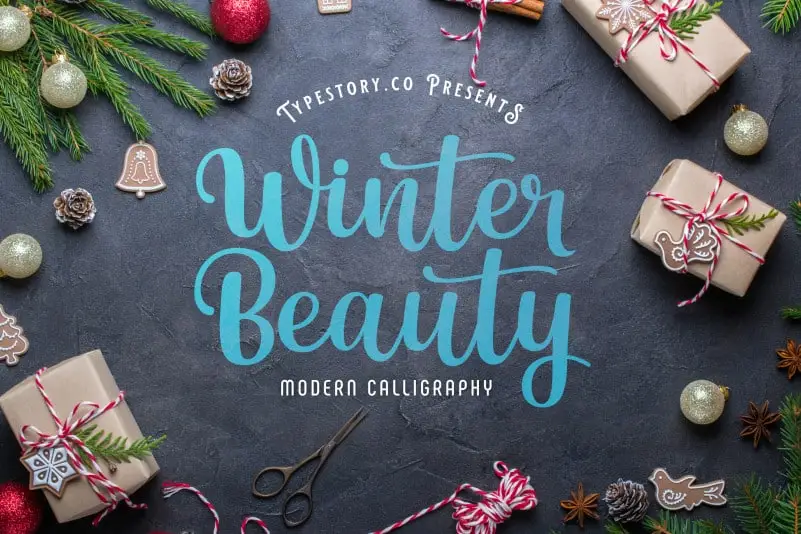
Winter Beauty Script Font – Download Grátis
Winter Beauty Script Font é uma fonte elegante e criativa ideal para quem busca arte sofisticada com texturas suaves. Essa tipografia retrata a beleza inusitada do inverno, transmitindo serenidade e romance através de suas formas redondas e encantadoras. Ideal tanto para o design de logotipo quanto para criações de marca modernas, esta fonte traz um toque único às produções gráficas. Adicionalmente, ela é perfeita para os mais diversos projetos, incluindo cartazes com citações, capas de livros ou capas de revistas, design editorial e até mesmo camisetas personalizadas. Sua utilização se estende também aos designs digitais, como páginas da web ou blogs. Seja você um designer digital ou um amante do papel, Winter Beauty Script Font trará vida a suas criações com o toque autêntico de uma escrita à mão livre. Com sua sofisticação e encanto, é um recurso indispensável para qualquer projeto que deseje destacar-se entre os demais.